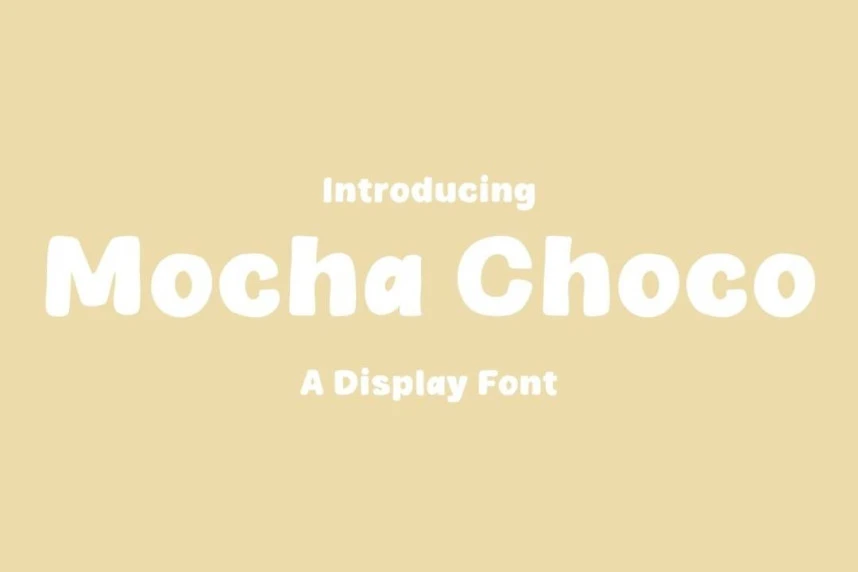
Mocha Choco Font, MJType tarafından tasarlanmış olup projelerinize tatlı ve neşeli bir kişilik katmayı amaçlayan, çizgi film tarzında bir gösterim yazı tipidir. Yuvarlak, baloncuk benzeri harf biçimleri ve yumuşak eğrileriyle eğlenceli bir hava çağrıştırır.
Mocha Choco Font, MJType tarafından oluşturulan eğlenceli bir karikatür tarzı gösterim yazı tipidir ve projelerinize tatlı ve neşeli bir kişilik kazandırmak için tasarlanmıştır. Yuvarlak, kabarık harf biçimleri ve yumuşak kıvrımlarıyla eğlenceyi çağrıştırır.